Вводите имя, выбираете цвет, скачиваете PNG. Вот и всё, уходит секунд десять.
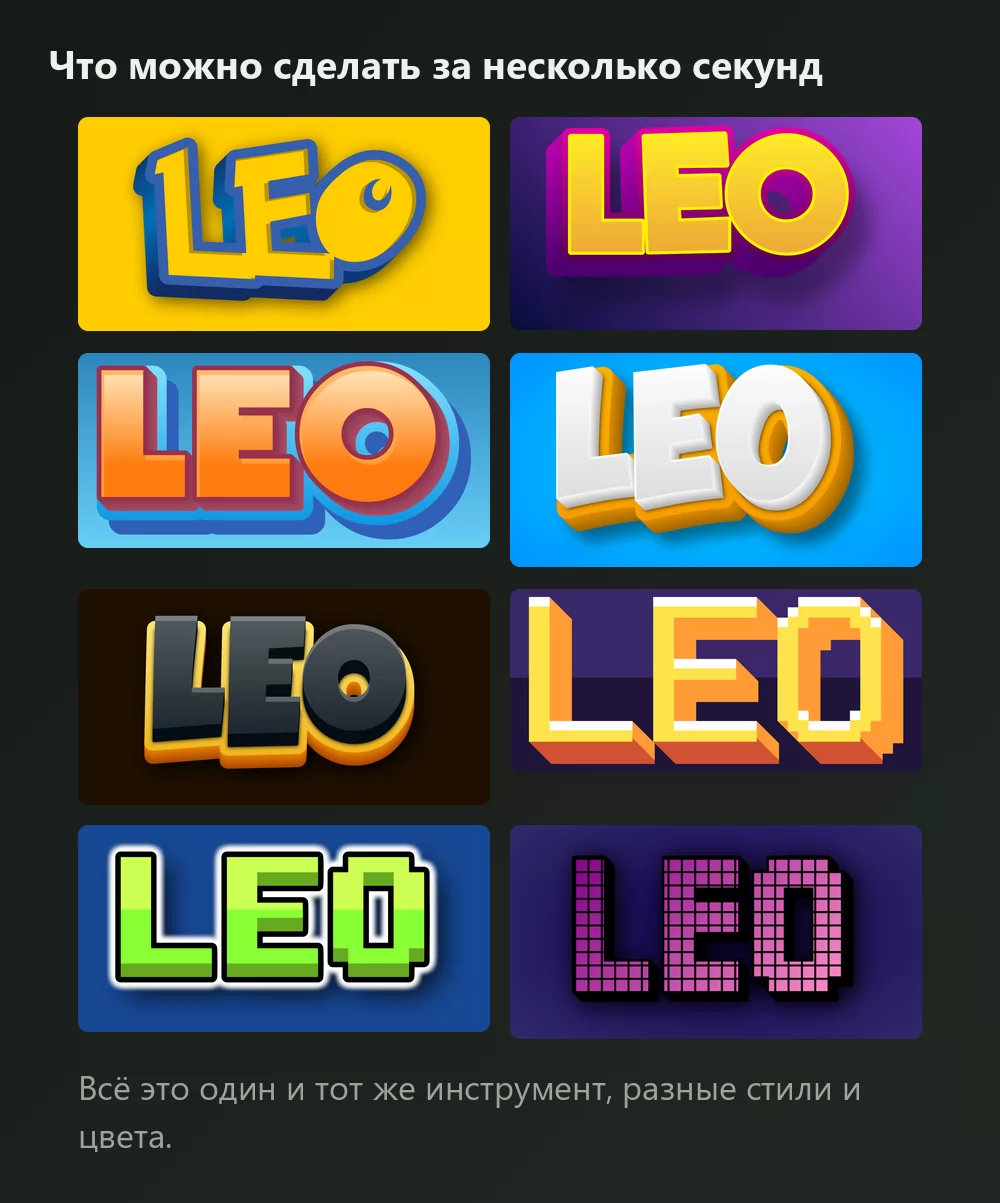
Всё это один и тот же генератор шрифта Pokemon, просто с разными стилями из списка. Ничего не устанавливается, аккаунт не нужен.
Как сделать текст в стиле Pokemon
Шаг 1. Введите имя
Откройте генератор и замените образец текста на свой: имя, команду, канал, заголовок. Буквы перерисовываются по мере ввода.
Шаг 2. Выберите цвета
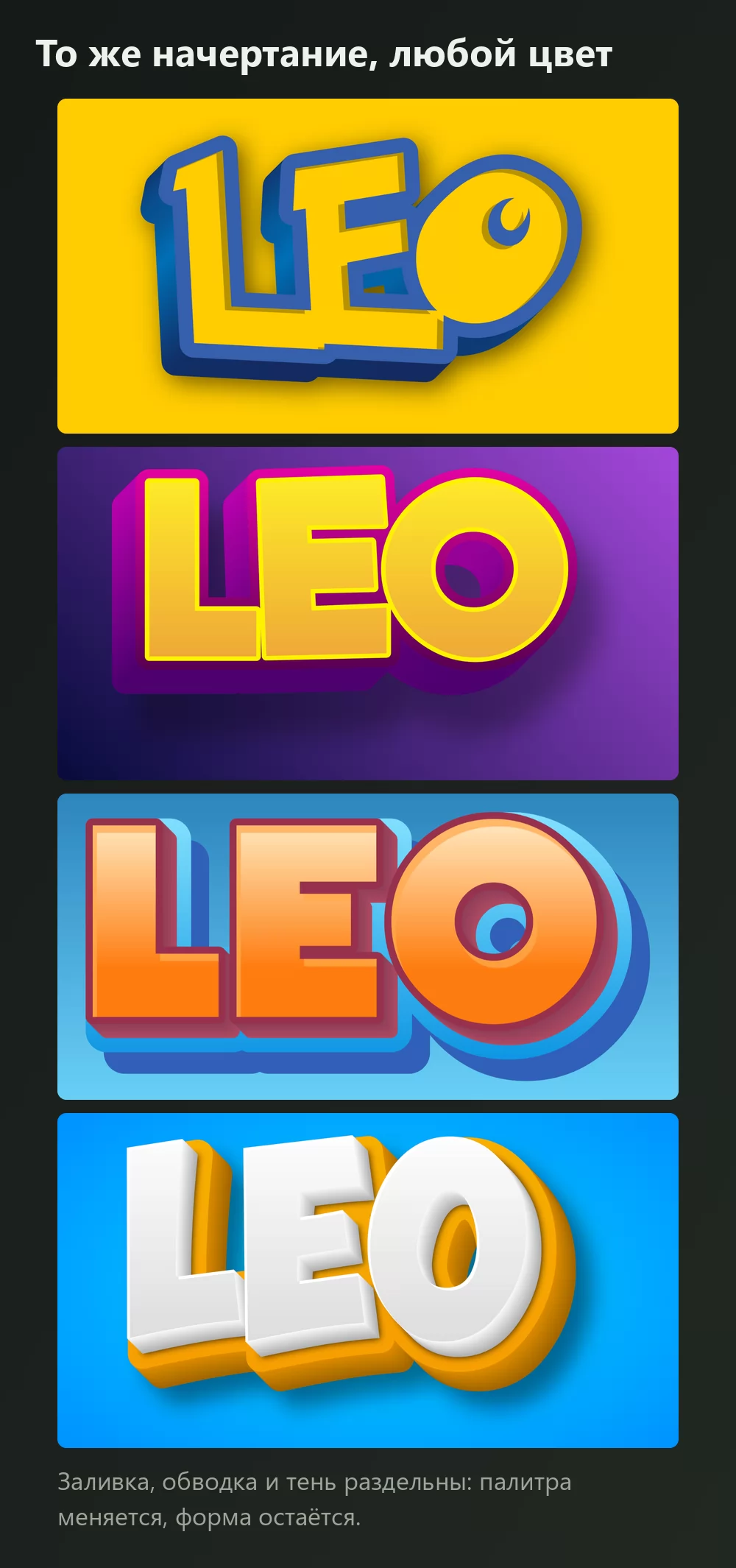
Во вкладке «Стили» три панели, и каждая делает своё:
- Объём и заливка отвечает за цвет самих букв: сплошной, градиент или узор.
- Обводки отвечают за кант, включая два вида объёмной обводки. Именно этот глубокий синий кант заставляет жёлтые буквы читаться как Pokemon, а не как просто жёлтое слово.
- Тени охватывают падающую, внешнюю и внутреннюю тень, с размытием и прозрачностью.
Жёлтый с синей обводкой это палитра сериала, но форма работает в любом сочетании.
Шаг 3. Выберите формат
Задайте формат до экспорта, и потом ничего не обрежется. 16:9 для превью видео, квадрат для аватара, широкая полоса для шапки.
Шаг 4. Скачайте
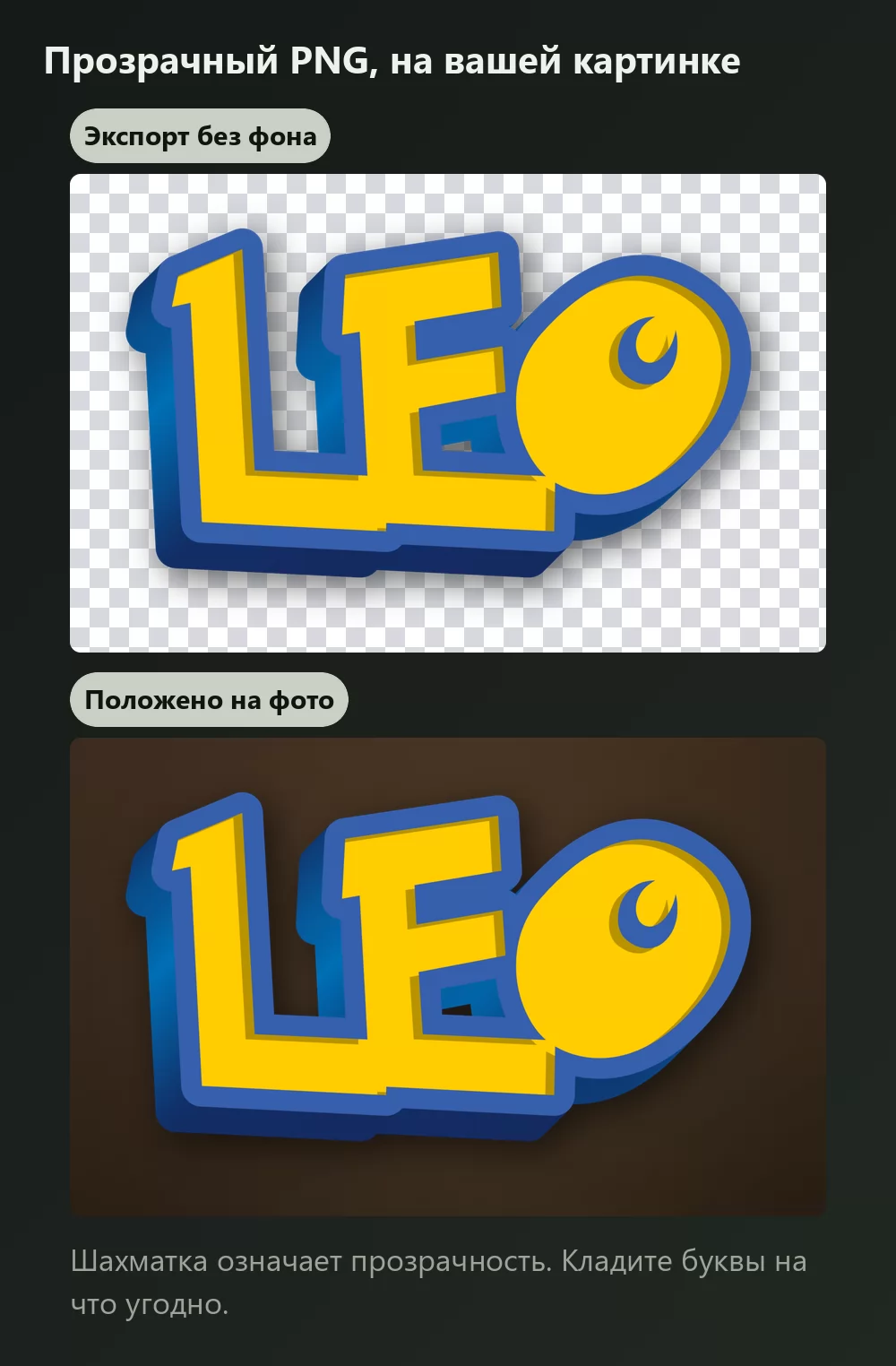
Во вкладке «Скачать» берите прозрачный PNG, если собираетесь класть буквы на свой скриншот, фото или превью. Именно эту опцию чаще всего пропускают, и именно она делает результат сделанным, а не приклеенным.
Длинные имена быстро занимают всю ширину
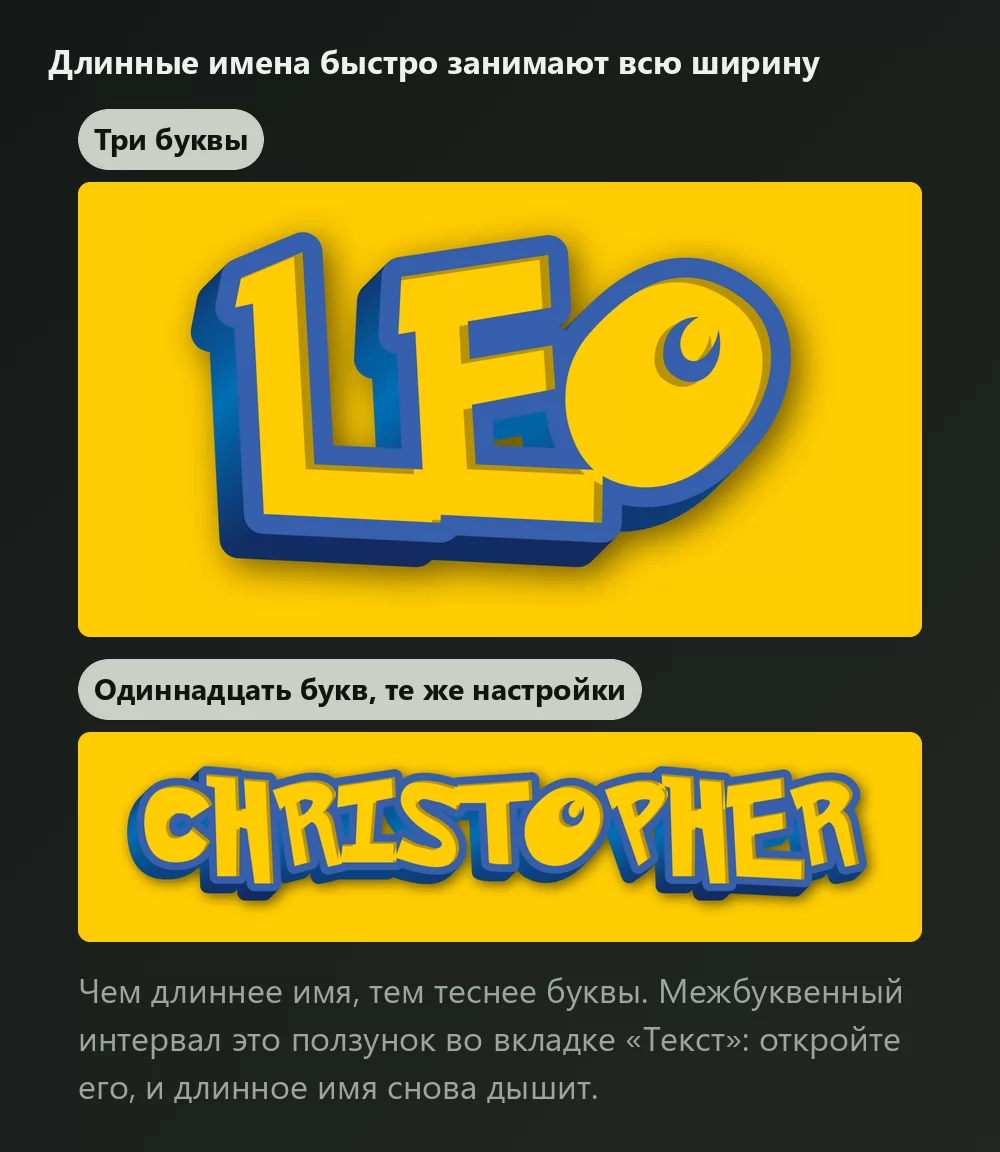
Чем больше букв, тем теснее они стоят. Межбуквенный интервал это ползунок во вкладке «Текст»: откройте его немного, и длинное имя перестанет выглядеть стиснутым. В той же вкладке лежат масштаб, межстрочный интервал, изгиб и поворот.
Изгиб текста
Ползунок изгиба и даёт заголовку упругость, и это разница между плоским словом и чем-то нарисованным. Нужно совсем немного: за определённой границей буквы расходятся веером и имя становится трудно читать.
Стиль логотипа или стиль игр?
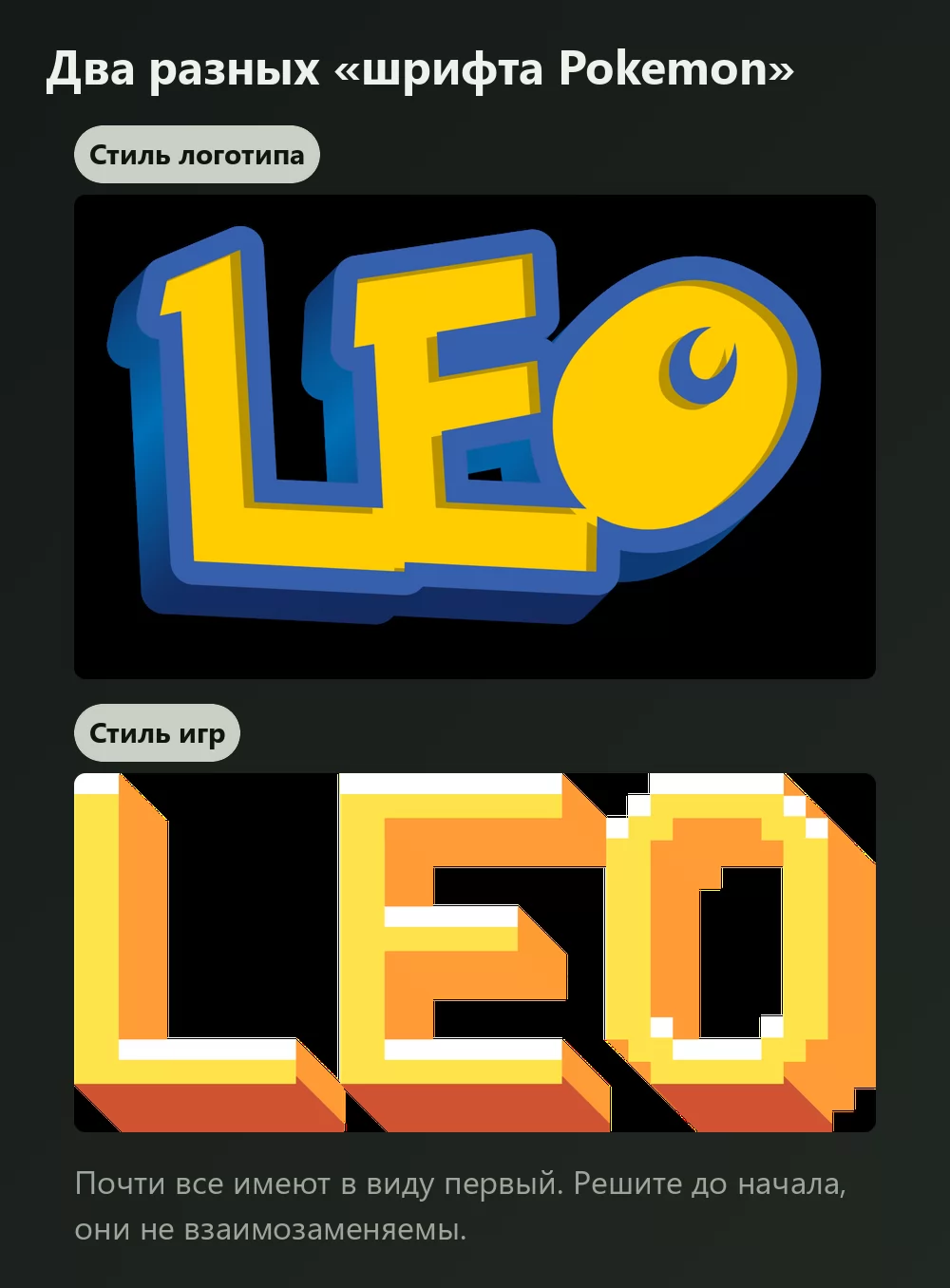
«Шрифтом Pokemon» называют две разные вещи. Почти все имеют в виду первую.
Стиль логотипа это толстые округлые буквы с плотной обводкой и небольшим объёмом, и именно его даёт генератор выше.
Стиль игр это мелкие пиксельные буквы портативных консолей. Если нужны они, вас туда приведёт пиксельный эффект в духе 8 бит.
Шрифт называется Pokemon Solid
- Pokemon Solid это залитая версия, нужная для заголовка.
- Pokemon Hollow это только контур, для крупных размеров, которые вы заливаете сами.
К чему стоит быть готовым: шрифт даёт формы букв и больше ничего. Синяя обводка, заливка, объём и тень это эффекты, которые вы потом строите сами, то есть ровно та работа, которую генератор делает за вас.
Другие шрифты Pokemon, о которых стоит знать
- Pokemon GB воспроизводит мелкий растровый шрифт игр для Game Boy. Подходит для поддельного диалогового окна, не подходит для заголовка.
- Pocket Monk это другое прочтение надписи логотипа, полезное, если Pokemon Solid не ложится.
- Pokemon Pixel Font угловатый, со ступенчатыми диагоналями, ближе к экрану аркадного автомата, чем к сериалу.
Все они фанатские копии. Официальная надпись рисовалась для бренда и шрифтом никогда не выпускалась.
Как сделать текст в стиле Pokemon в Canva
Как сделать текст в стиле Pokemon в Photoshop
Установите Pokemon Solid, наберите текст, затем соберите обработку стилями слоя:
- Обводка, снаружи, глубокого синего цвета, довольно толстая.
- Наложение градиента или сплошная жёлтая заливка для букв.
- Тень, со смещением вниз и чуть вправо, с низкой непрозрачностью.
Это подводит близко. Объём настоящего логотипа получается из дублированного слоя, сдвинутого за первым, и его трудно держать ровным по всем буквам.
Как сделать текст в стиле Pokemon в Word
Установите шрифт, наберите текст и задайте обводку и тень через эффекты текста. Эффекты Word намного грубее, чем в графическом редакторе: для всего, что пойдёт в печать или в публикацию, экспортированный PNG будет выглядеть лучше того, что Word умеет собрать.
Почему мой текст не похож на логотип даже с нужным шрифтом? Потому что шрифт это только формы букв. Синяя обводка, объём и тень это эффекты, наложенные сверху.